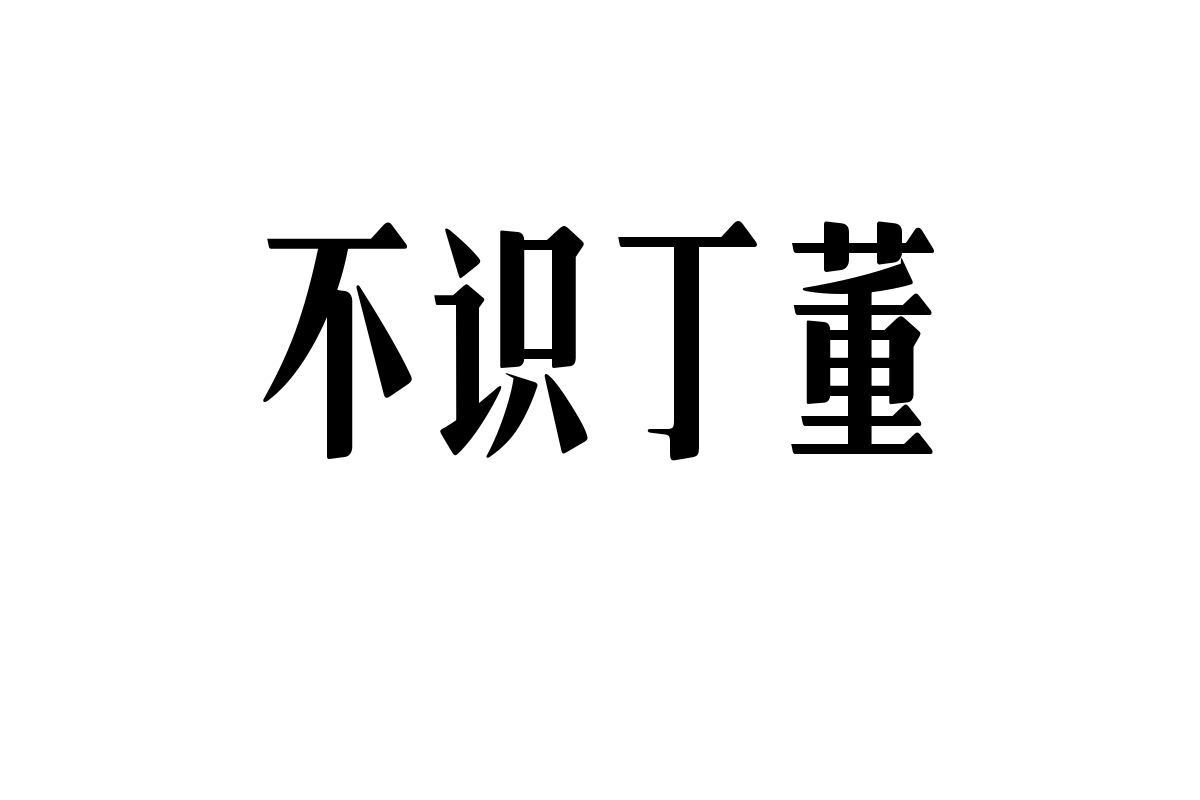
也字工厂港风宋体是一款具有独特风格的中文字体,它结合了现代和传统元素,给人一种时尚、现代的感觉。这款字体的笔画流畅,结构紧凑,适合用于各种需要展示个性和创意的设计项目。它的设计灵感来源于香港的街头文化,因此也带有一种独特的港风气息。无论是用于广告、海报、网页还是其他任何需要文字的地方,也字工厂港风宋体都能为你的创意增添一份独特的魅力。